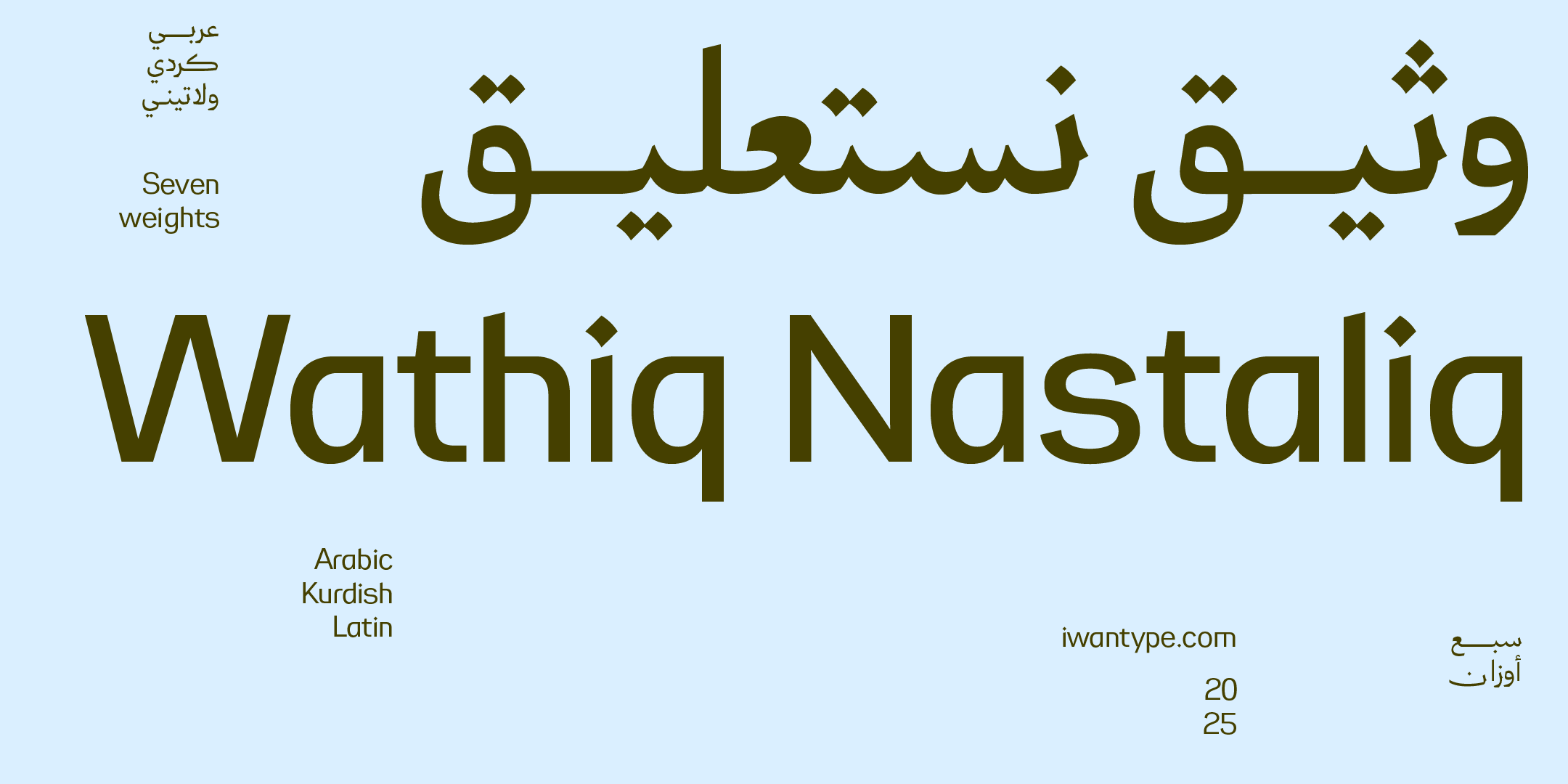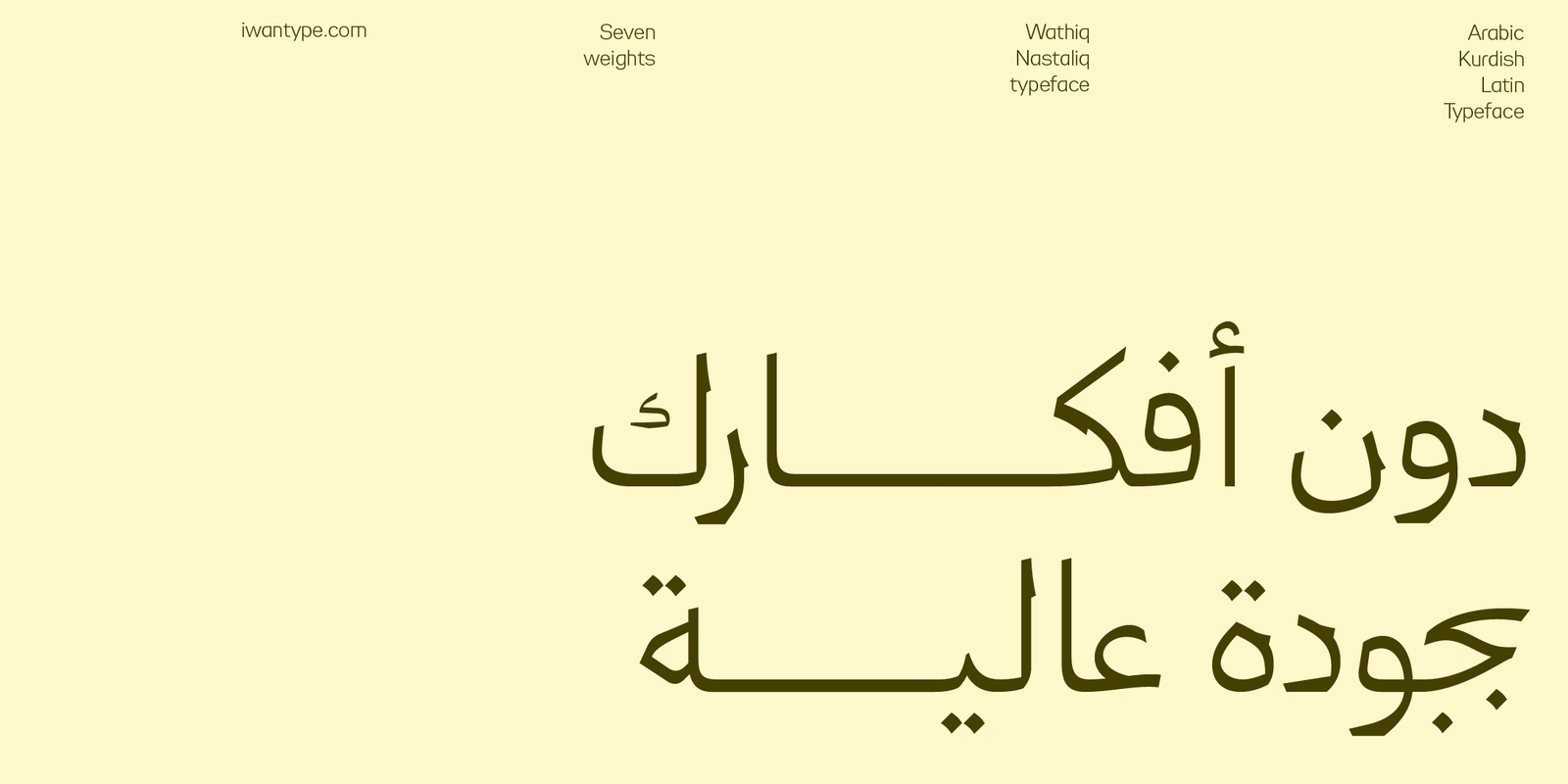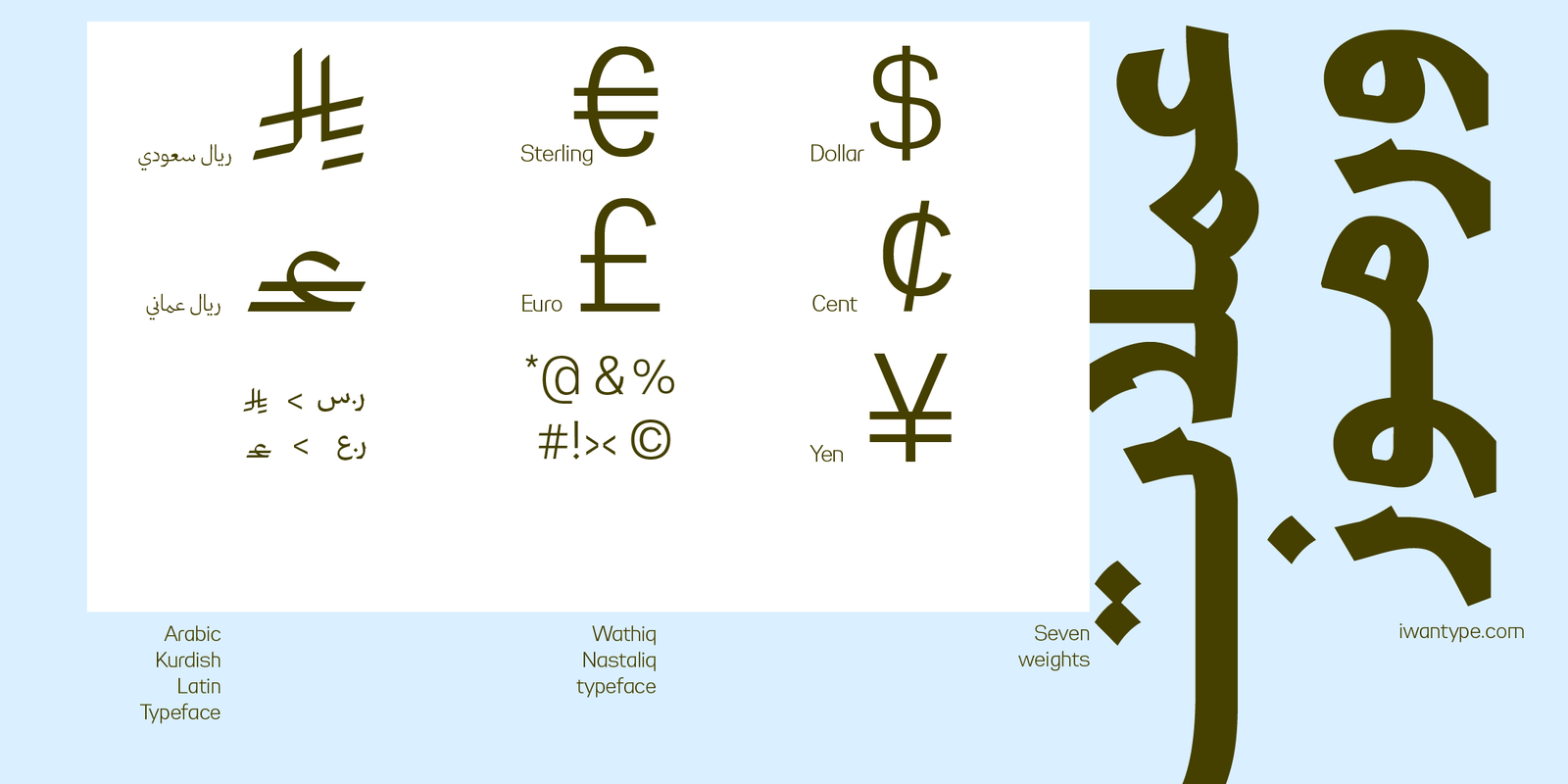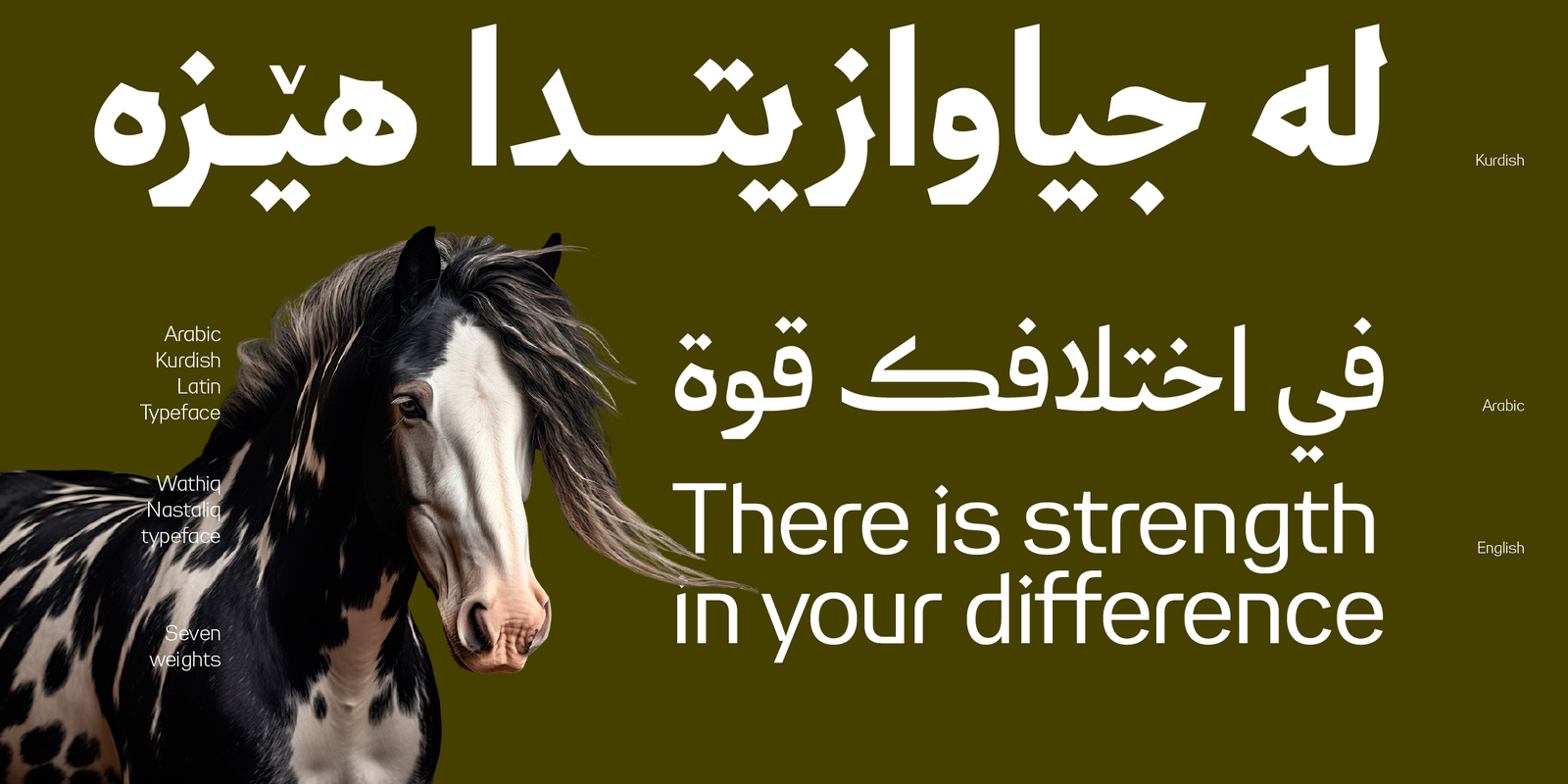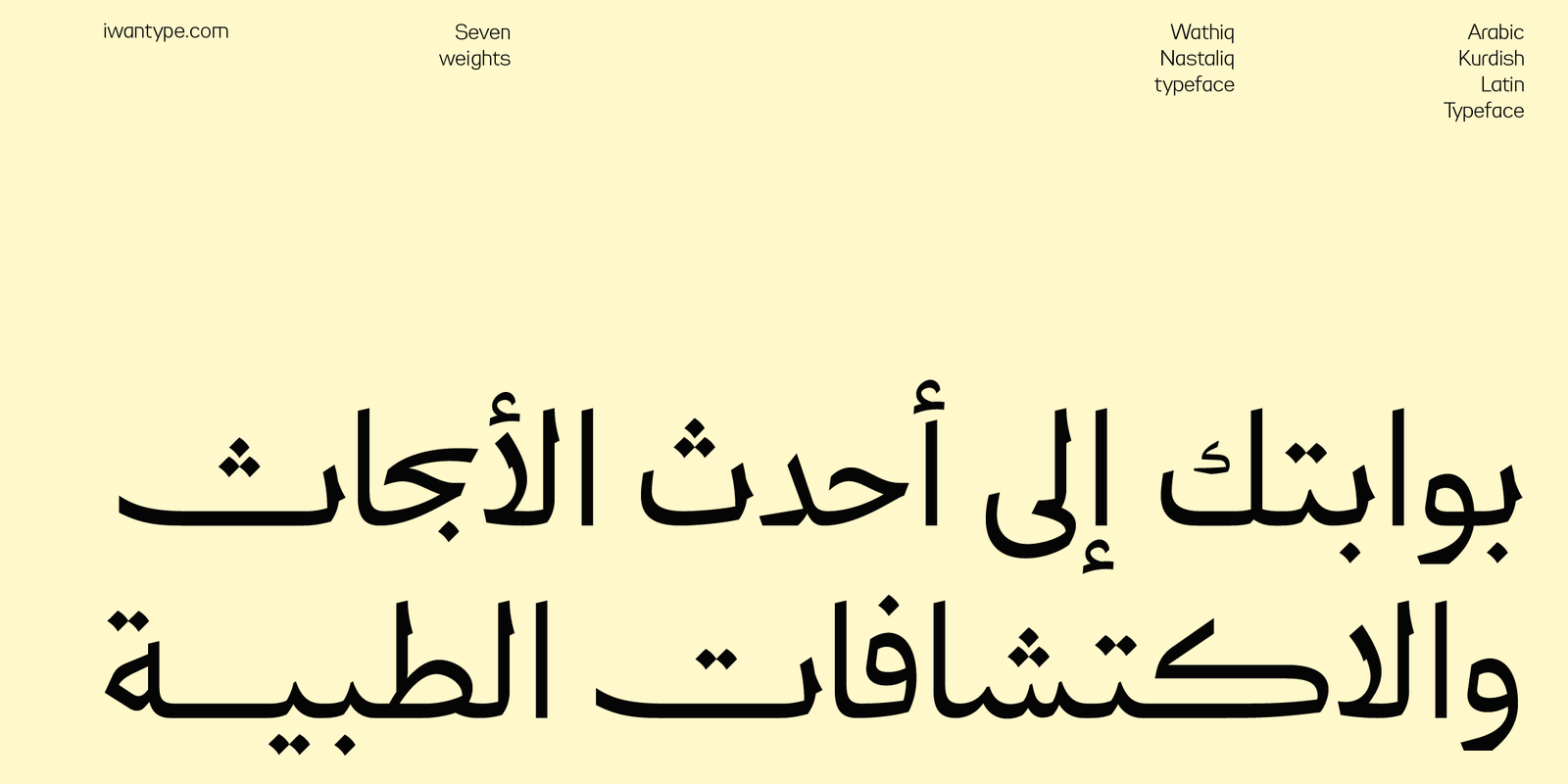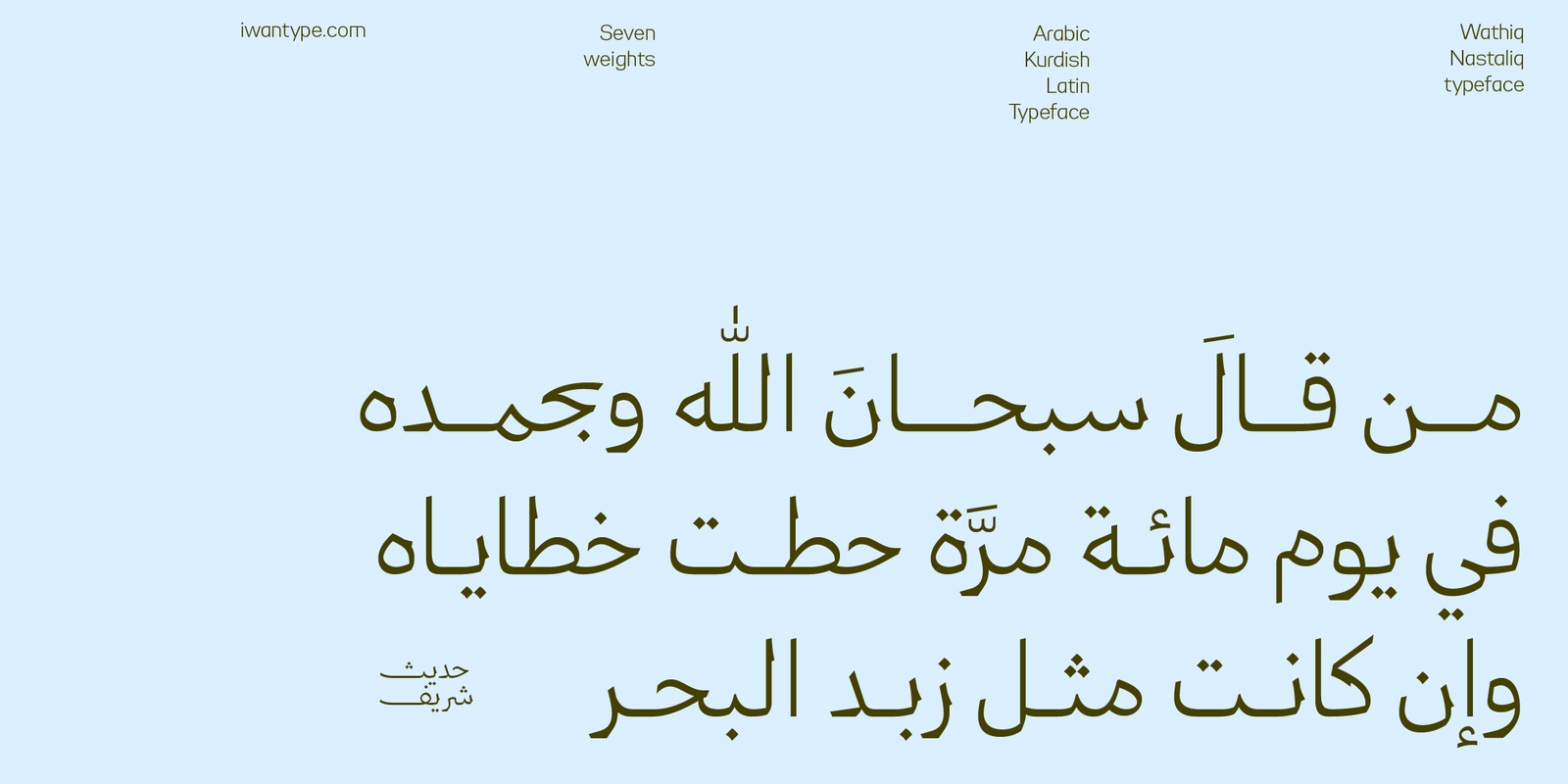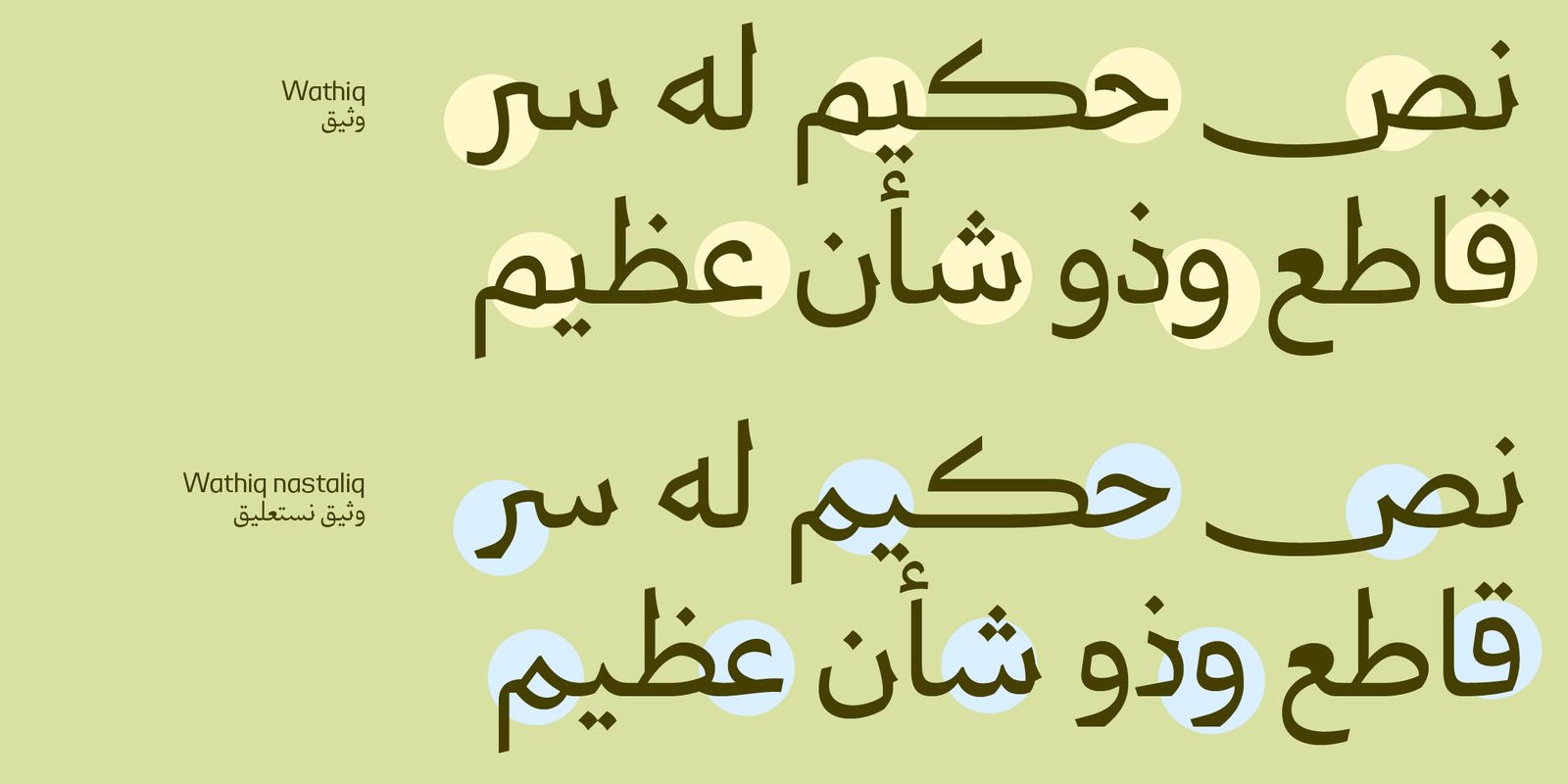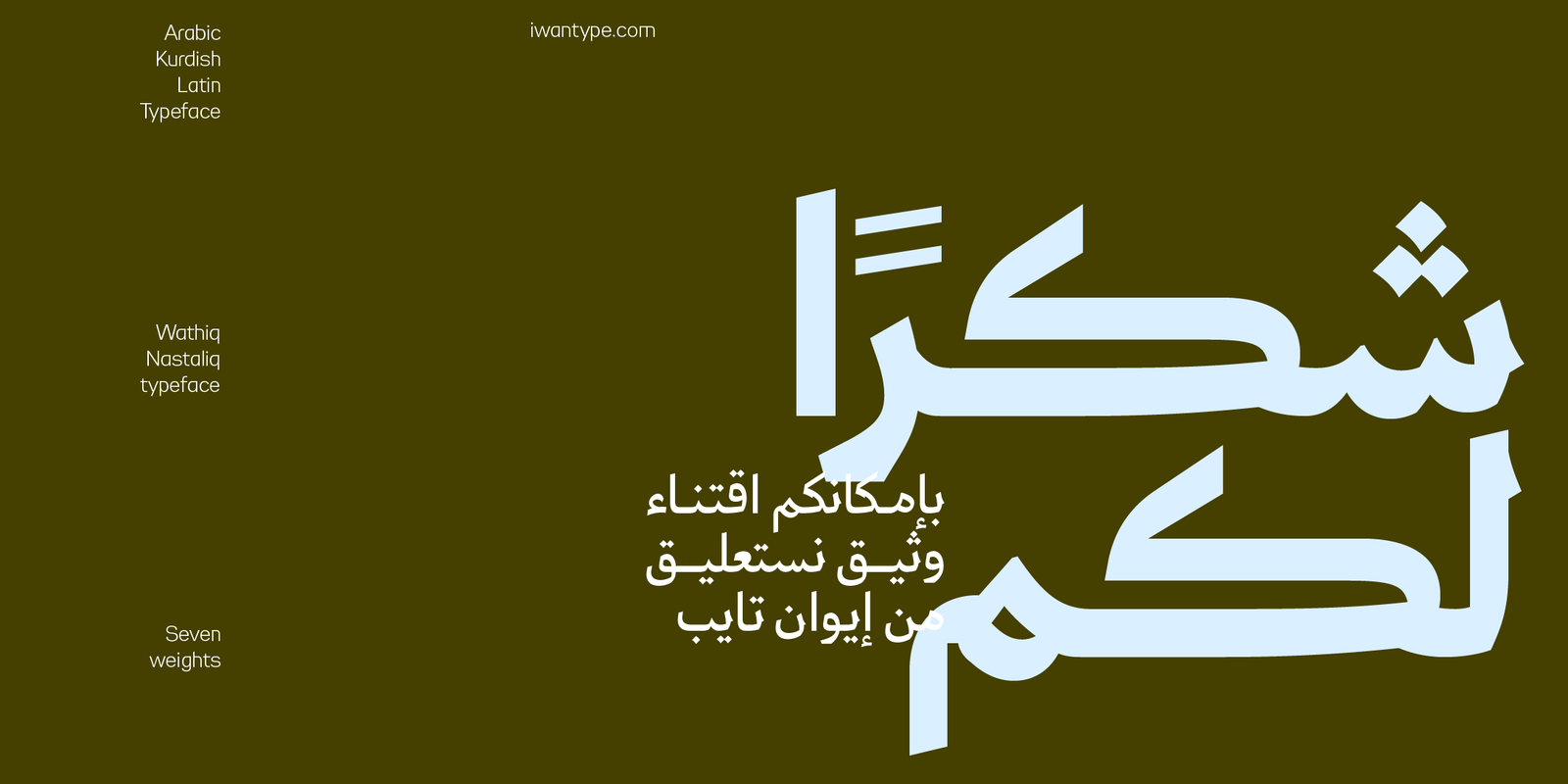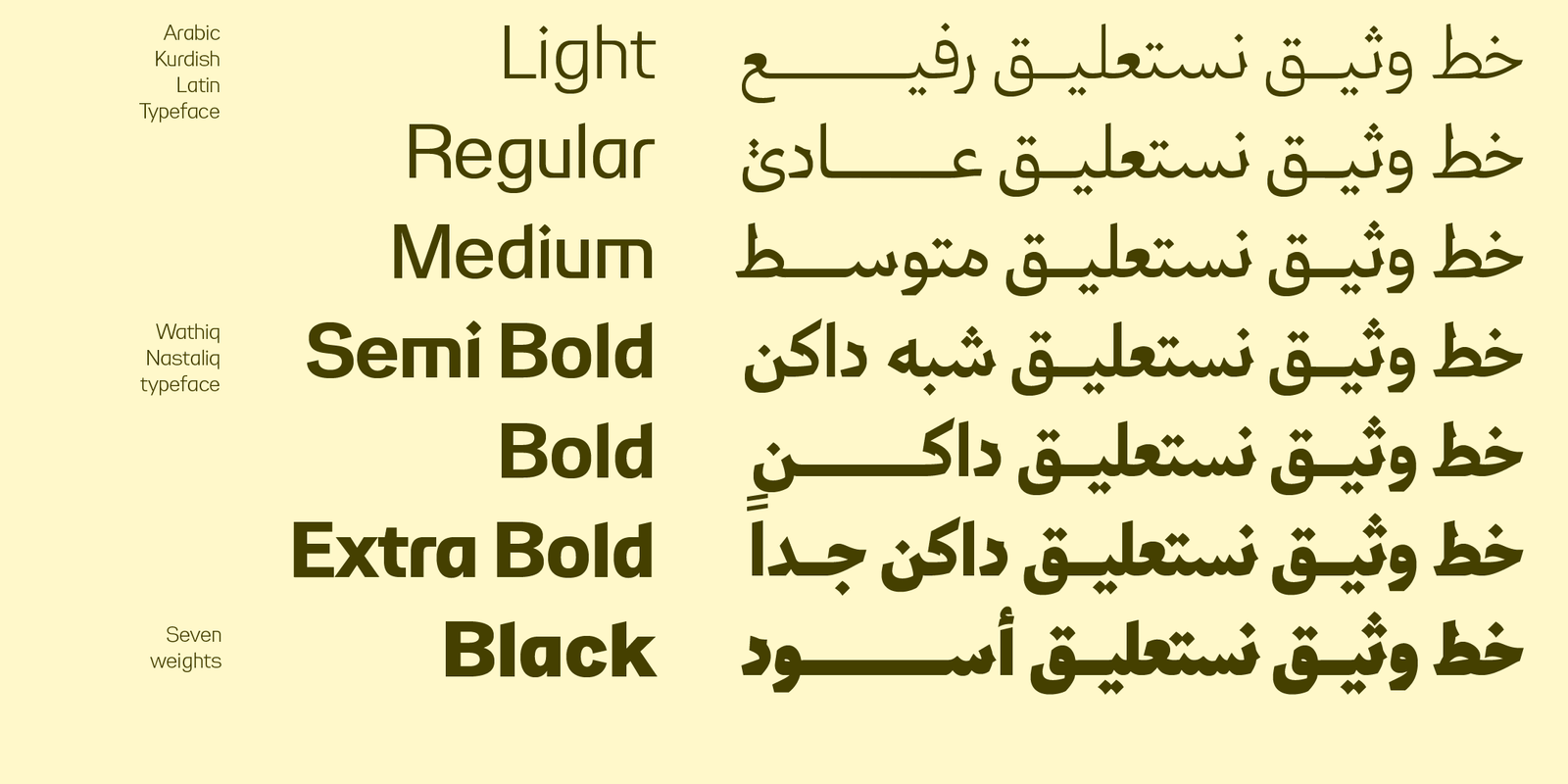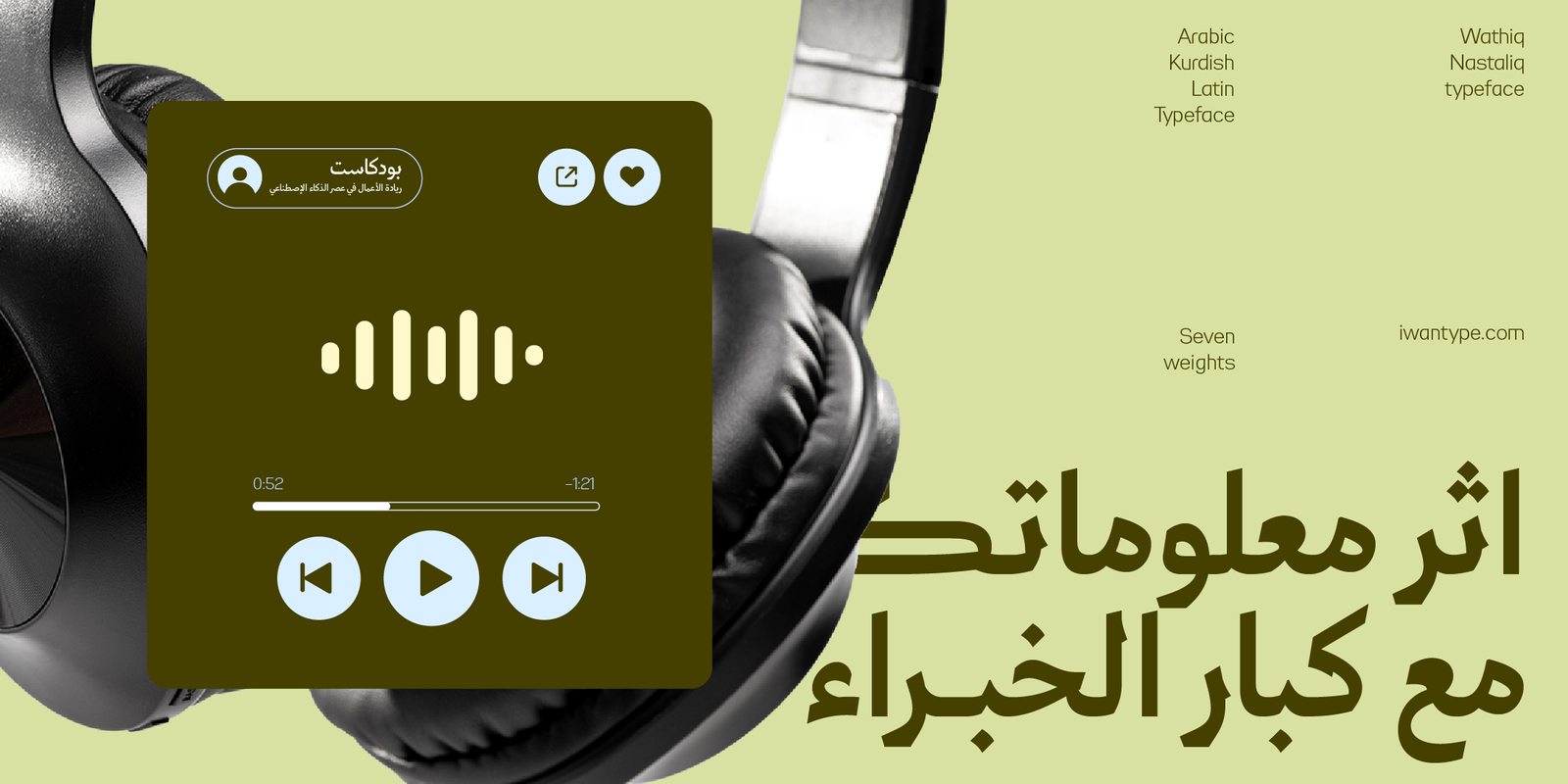
وثيق نستعليق – Wathiq Nastaliq
خط وثيق نستعليق هو امتداد معاصر لعائلة وثيق، يجمع بين وضوح الخط النسخي ورشاقة النستعليق في صياغة بصرية هادئة ومتزنة. يقدم الخط حلولًا طباعية للمشاريع التي تبحث عن حضور هادئ بعيدًا عن الفخامة المفرطة، مع الحفاظ على قوة التعبير البصري.
الطابع التصميمي
يتميز وثيق نستعليق بانسيابية محسوبة تستلهم جماليات النستعليق دون محاكاتها التقليدية، فيما يحافظ على وضوح النسخ في بنيته الأساسية. النتيجة خط يتسم بالسلاسة والاتزان، مناسب للهويات البصرية والمشاريع الثقافية والإبداعية التي تحتاج إلى صوت طباعي معاصر وغير متكلف.
نطاق الاستخدام
صُمم الخط ليؤدي بكفاءة في العناوين والنصوص البارزة، سواء في التصاميم المطبوعة أو الرقمية. يناسب المؤسسات الثقافية، دور النشر، الهويات التجارية الراقية، والمشاريع الإبداعية التي تسعى إلى تحقيق توازن بين الأصالة والحداثة.
مميزات خط وثيق:
يتضمن الخط العديد من مزايا OpenType التي تضفي عليه مرونة وتنوعًا في الاستخدام، مثل:
- أحرف مرسلة (تُفعَّل بإضافة “ءء” بعد الحرف)
- حرف ياء بنزول أقل: يقلل من نزول السطر، مما يعزز من انتظام النصوص.
- أحرف المركبة: تسهم في تحسين المظهر العام للنص وتزيد من سلاسته.
- نقاط بديلة
- يدعم رمز الريال السعودي، ويمكن تفعيله بإضافة حرف “ء” بعد كتابة كلمة “ريال”.